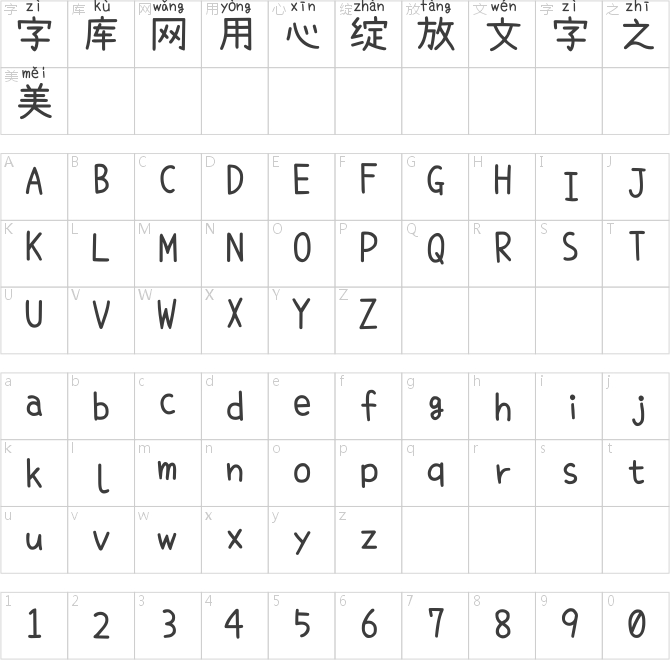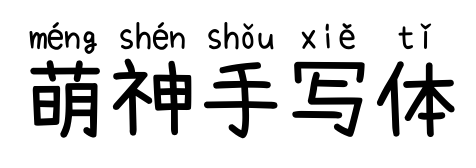
字體名稱: 萌神手寫體
萌神手寫體
萌神手寫體介紹
萌神手寫體是用于學習中國漢字的一款字體,是使用小賴字體進行改造而成的一款免費商用字體。 這是一種用來幫助學生更快地學習和閱讀漢語的字體。基本上是可以顯示日語、簡體字和繁體字的字體,是在簡體字和繁體字中加入拼音的字體的制作。
萌神手寫體字體Mengshen-Handwritten字庫是一款讓人賞心悅目、百看不厭的中文字體,適合各類廣告和產品包裝設計應用,字體大小18.74MB,格式為ttf字體,上傳用戶是23KUN,作者/版權方為MaruTama